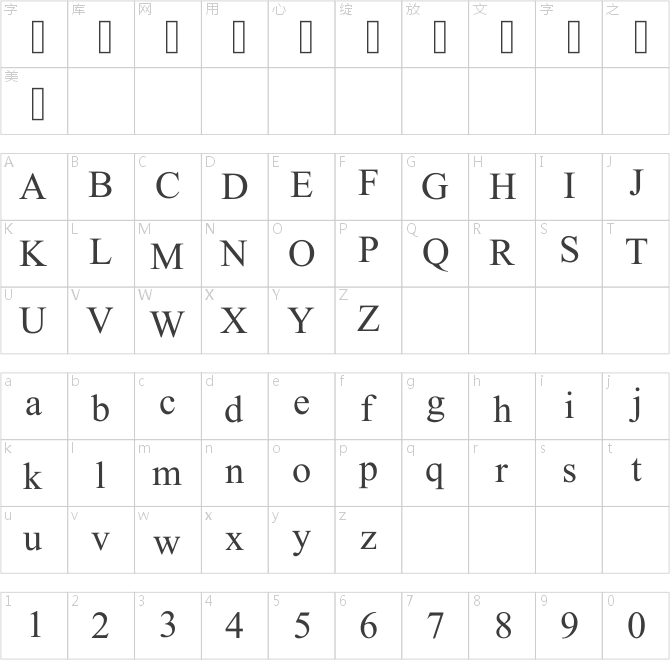
?????????????????????????? 詳情頁
迷藍藏文藝術(shù)
迷藍公司董事長次仁扎西表示,公司始終把培養(yǎng)合格社會主義建設者和接班人作為根本任務,為廣大高校畢業(yè)生提供就業(yè)擇業(yè)平臺,目前我公司就業(yè)帶動34人,其中大學生占27人。在過去三年的時間里公司專注于藏文藝術(shù)體的研發(fā),始終秉承以人民為中心的創(chuàng)作導向,堅持創(chuàng)作無愧于時代的優(yōu)秀作品,此次面向社會共發(fā)布了14種字體,分為兩種類型:傳統(tǒng)型字體與藝術(shù)型字體,整個字體的考察、收集、研發(fā)、編輯到錄入,工程為期將近三年左右,其參考了桑耶寺的石碑字體及布達拉宮的壁畫字體等。